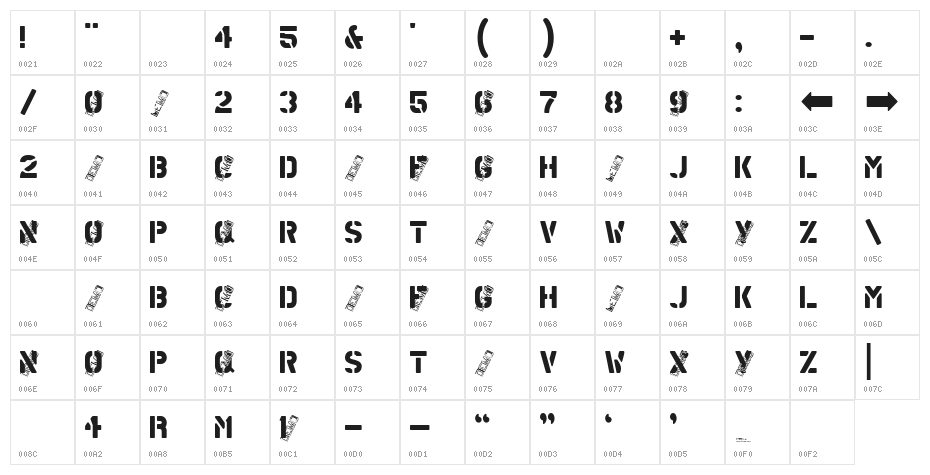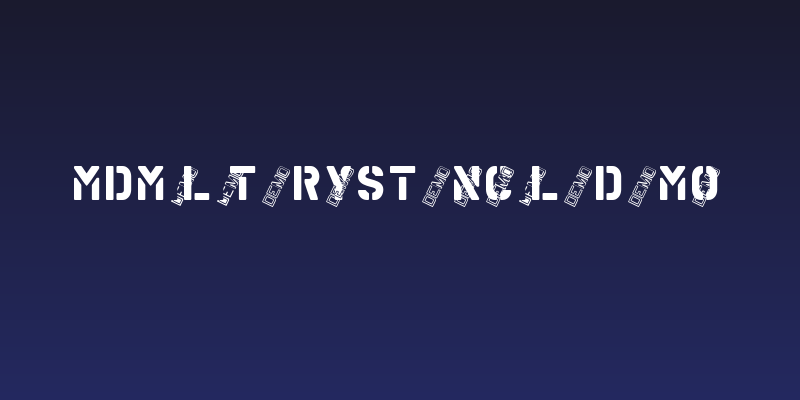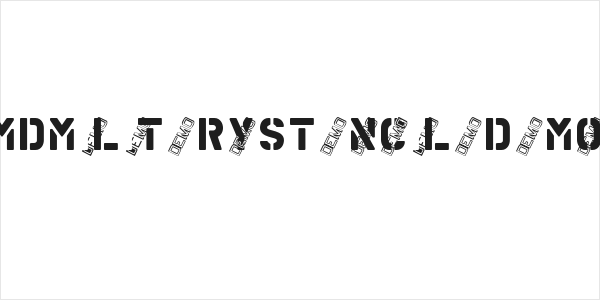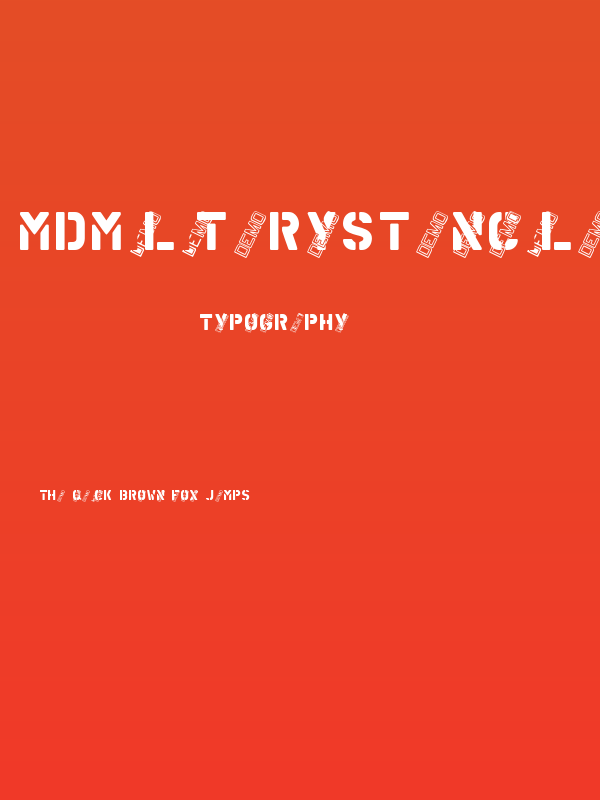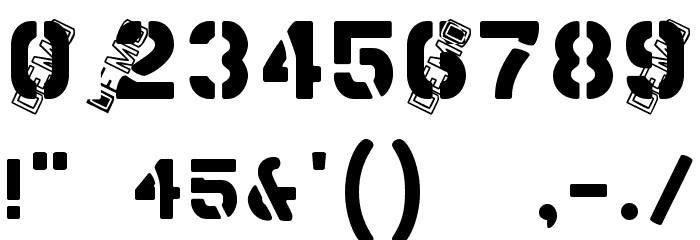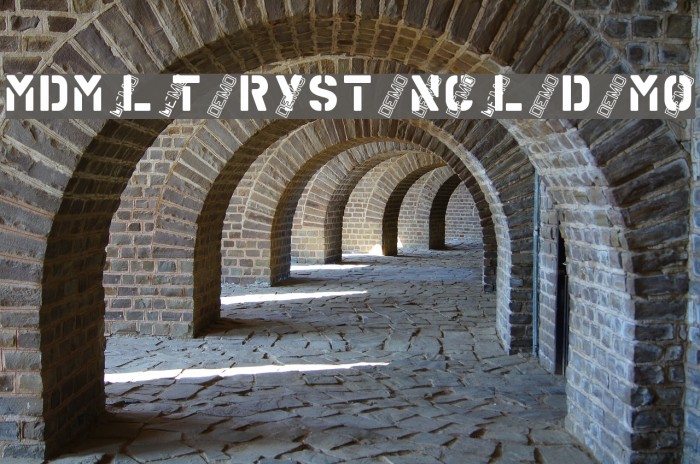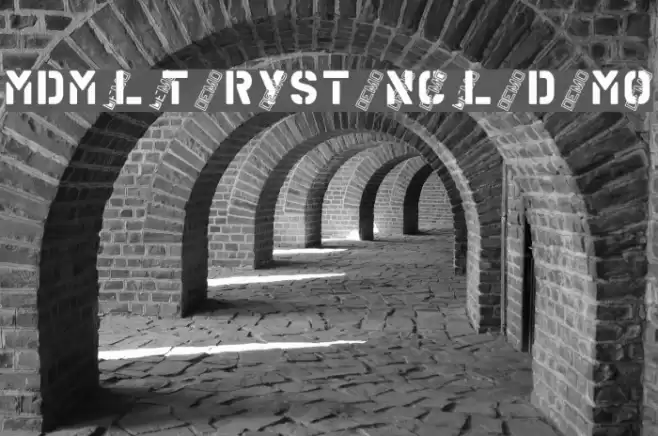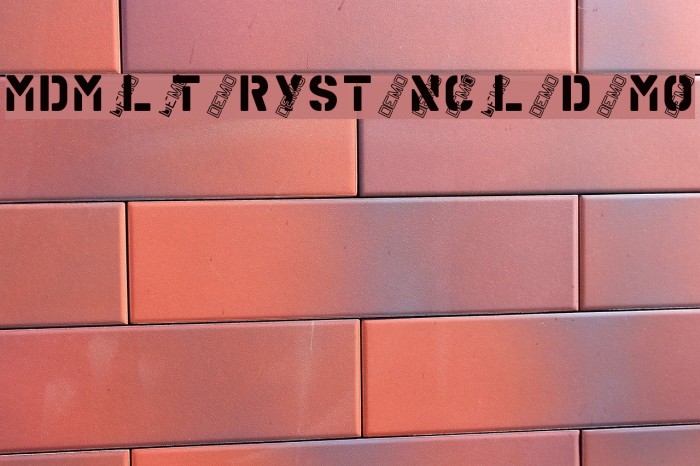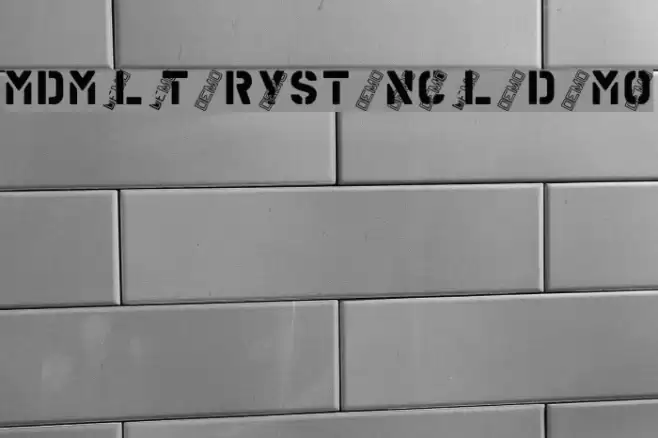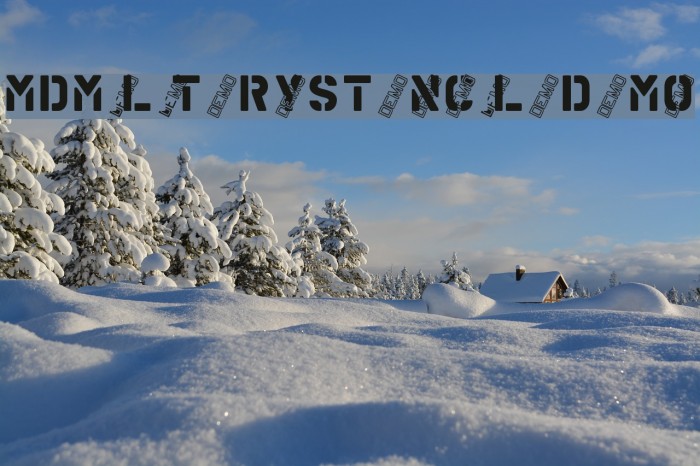
MDMilitaryStencilADemo Font
✎ Stencil
| समग्र शैली | Industrial, Military |
| उपयोग का मामला | Headlines, Logos, Signage |
| सुझाए गए प्रोजेक्ट | Ideal for military-themed designs, industrial branding, posters, signage, and any project requiring a strong, authoritative look. |